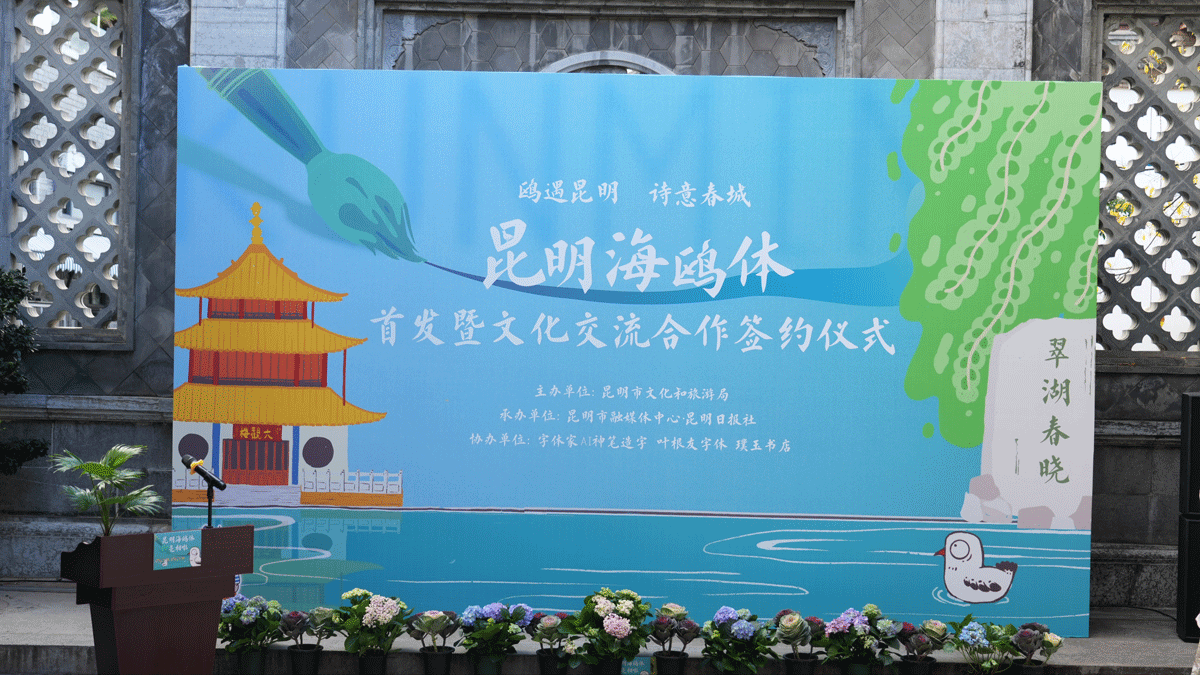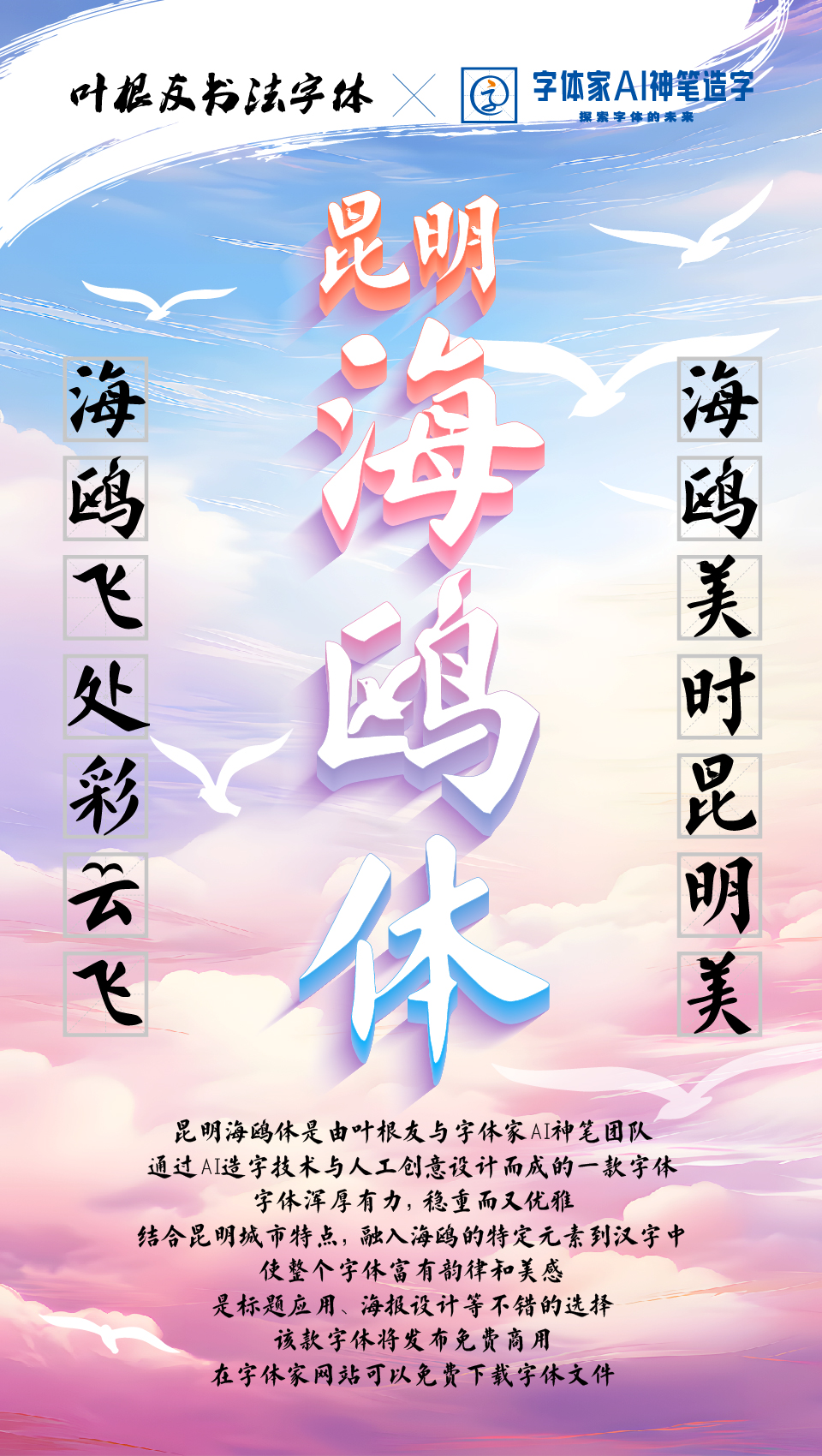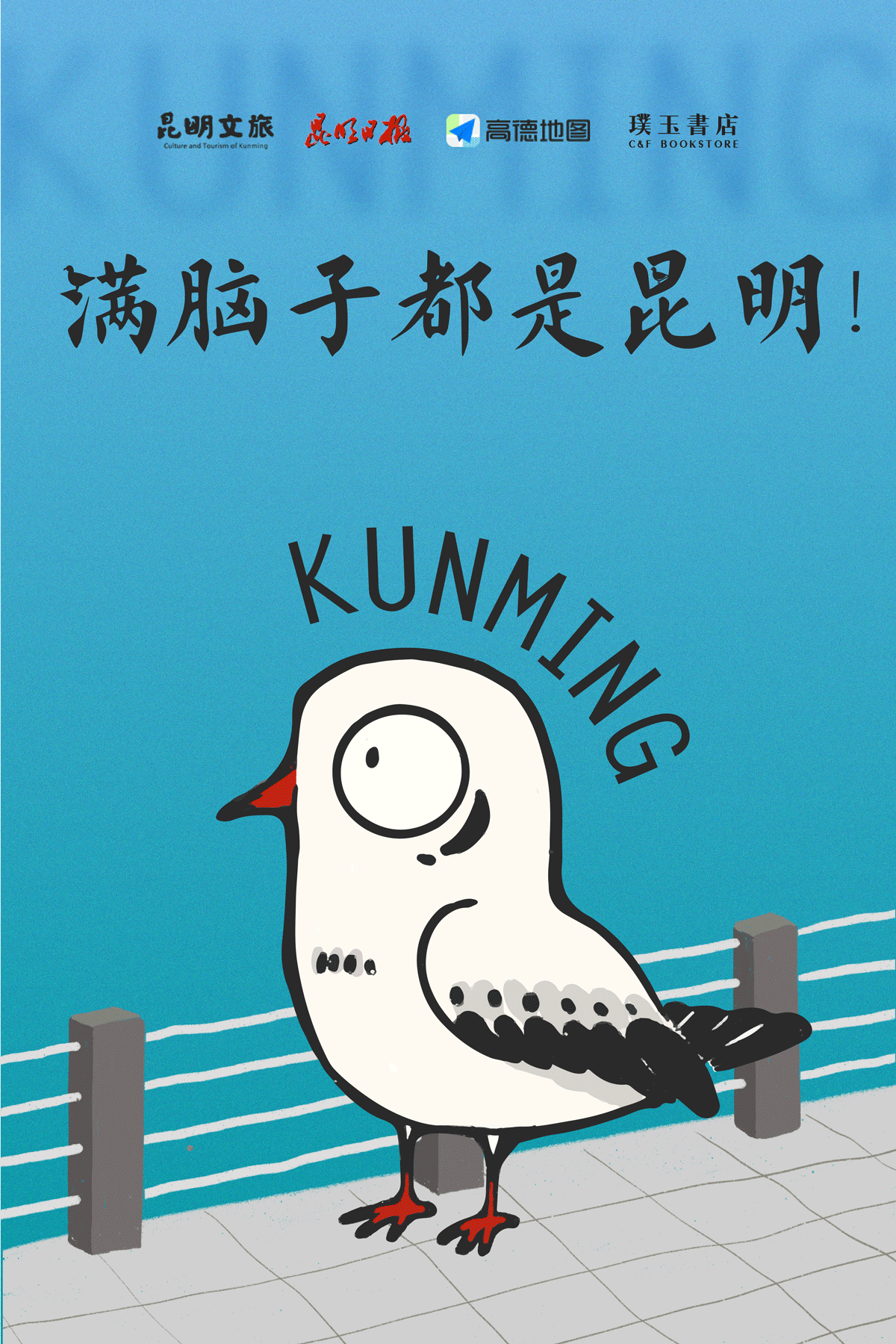
1月2日,“昆明海鸥体”首发暨文化交流合作签约仪式在昆明老街举行。“昆明海鸥体”创作者、字体家AI神笔造字负责人、中国当代著名书法家叶根友为昆明送上专属的新年文化礼物——全国首款城市定制型海鸥主题字体。这款被命名为“昆明海鸥体”的字体,全套共6763个字,即日起就可供全国设计工作者免费使用。
活动上,叶根友与昆明市文化和旅游局签订了“昆明海鸥体”版权转让协议,把这份专属的新年文化礼物——全国首款城市定制型海鸥主题字体赠送给了昆明市。他还现场书写了今年观鸥季的主题“鸥遇昆明 诗意春城”,赠送给昆明市融媒体中心。
叶根友介绍,昆明海鸥体先后经历了六版的更新升级。“我们观察了红嘴鸥起飞、降落、飞翔、觅食等的形态,并将这些形态记录下来,再一次次和汉字笔画融合。”
昆明市文化和旅游局副局长王明瑶表示,叶根友独具匠心的创作,为昆明这座城市增添了一份独特的文化魅力。从1985年开始,每年冬季,大批红嘴鸥不远万里飞抵昆明,“人鸥同乐”的画面早已成为昆明的冬日风景线和城市名片。2025年刚好是“人鸥结缘40载”,叶根友创作的“昆明海鸥体”,将海鸥元素融入书法中,既展现了书法的神韵之美,又彰显了昆明的观鸥风情,为昆明观鸥季赋予了独特的文化内涵。今后,通过“昆明海鸥体”的发布和推广,能够吸引更多的游客前来感受春城的魅力,体验“有一种叫云南的生活”。
将海鸥的姿态和汉字融合,并不是一件易事。“每一个字不仅要有海鸥的灵动,也要有汉字本身的美感。“我们努力地创作,就想让昆明本地人一眼看出,有只红嘴鸥‘落’在了汉字上。让外地人通过字体来了解人鸥和谐相处40年的故事。”叶根友说。
叶根友及其团队又通过海量的模拟找到最合适和海鸥形态相结合的汉字笔画。通过两个月的不断尝试,让昆明海鸥体字体隽秀且不失稳重典雅,有碑帖中的古碑神韵,也有现代书风的气息,不仅符合现代人简约时尚的审美理念,作为全国首款融入红嘴鸥元素的字体,生动且有趣。
“昆明海鸥体”的“昆明”两字中的都有红嘴鸥的形象,特别是“昆”字中的红嘴鸥形象,设计团队先后做了10多种造型,最后才选定一只站立红嘴鸥的形象。除了昆明两字中有海鸥形象之外,“滇池”“春城”“翠湖”“平安”“美满”等汉字的笔画中都有红嘴鸥的各种姿态。
“昆明海鸥体”是一款书写很新颖的字体,字体大方,适合各种设计作品使用!欢迎下载!